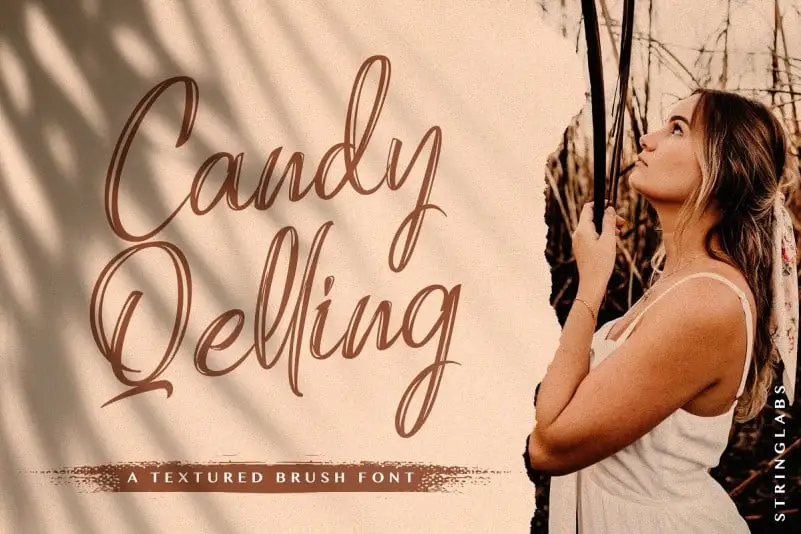
Candy Qelling Brush Font – Download Grátis
A Candy Qelling Brush Font é uma excelente opção para quem busca um estilo elegante e fluido no seu próximo projeto. Esta fonte é agradavelmente escrita a mão, com um toque delicado que encaixa perfeitamente com qualquer estilo favorito. Ela foi projetada pelo designer StringLabs e criada utilizando uma caneta à espreita, resultando em um design suave e elegante. Se você estiver procurando por algo novo para adicionar ao seu trabalho de design, a Candy Qelling Brush Font pode ser justamente o elemento que precisa. Ela consegue capturar a essência de projetos criativos com sua personalidade única e bela, tornando-a uma escolha conveniente para qualquer aplicação visual. Seja um site pessoal, uma identidade de marca ou até mesmo uma revista digital – essa fonte se adaptará perfeitamente à sua necessidade. Não hesite em adicionar a Candy Qelling Brush Font aos seus projetos, ela certamente traz vida e sofisticação para qualquer design que você criar.